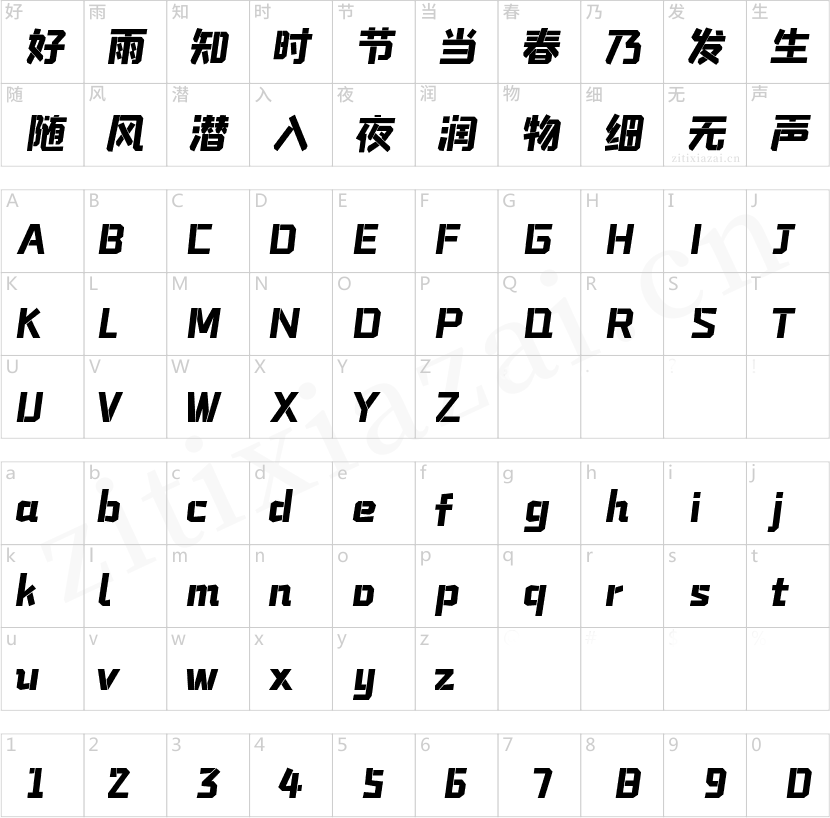
字魂机甲超级黑
字魂机甲超级黑,这款字体结构工整、笔画清晰,兼顾美观与易读性,适用于标题、正文、海报、包装、LOGO 等多种场景。字形优雅稳定,风格百搭耐看,适配日常排版与创意设计,让文字呈现更舒适、更具质感。字魂机甲超级黑一笔一画,皆是细节,以均衡的比例、流畅的线条打造舒适视觉体验,字形端正大气,风格简约现代。无论是商业设计、品牌宣传还是日常排版,都能轻松驾驭,让文字更有格调与力量。字魂机甲超级黑字体下载。